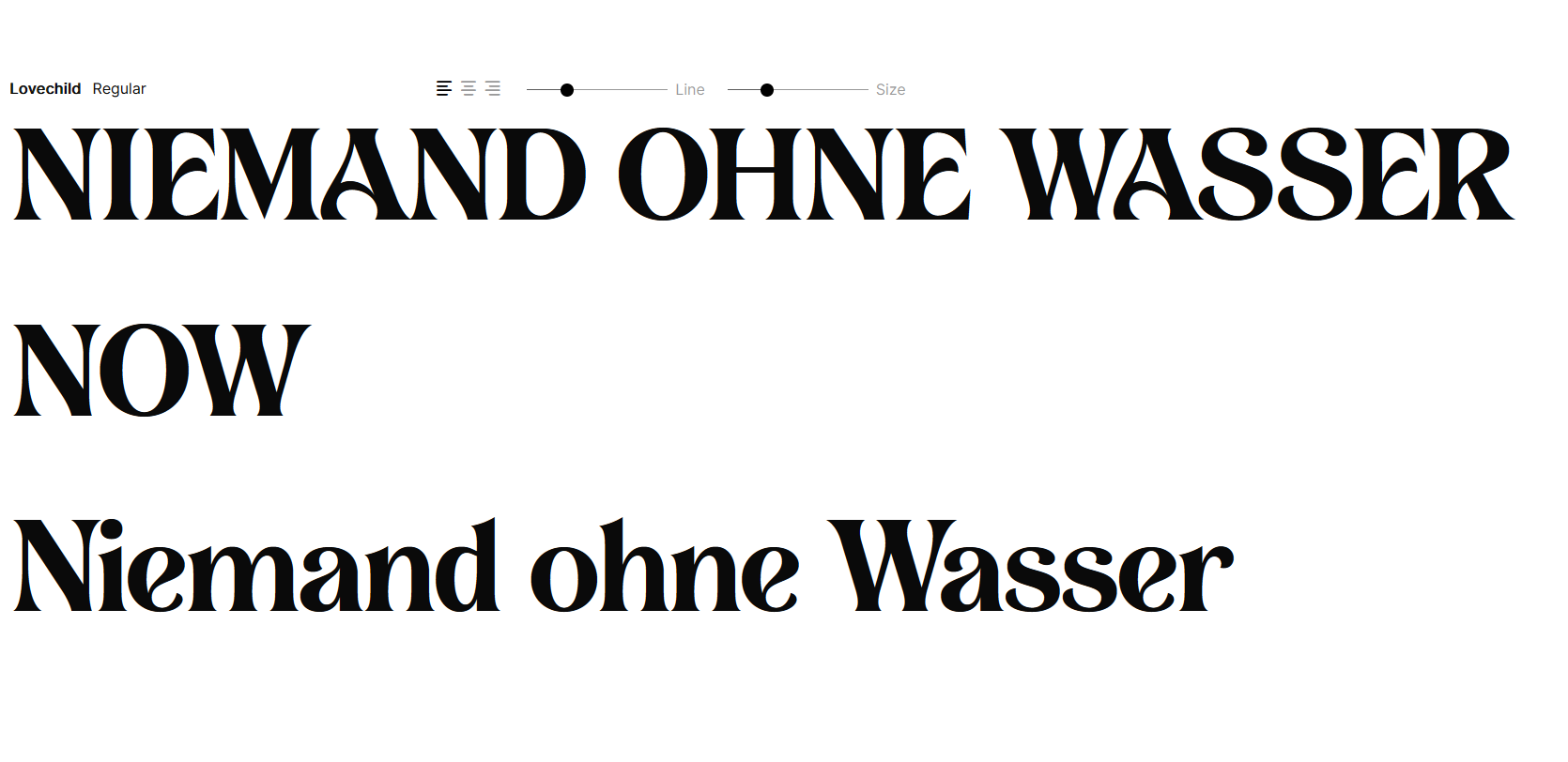
Plakative Logo-Schrift Thema Wasser.
ich mache über das Studium (Erst- bzw. Zweitsemester 😅) zusammen mit zwei Kommilitoninnen an einem Pitch mit. Das Thema ist "Wasser für die Welt". Unser Slogan lautet "Niemand ohne Wasser - NOW" . Wir würden uns freuen, wenn ihr einen Tipp für die Typo habt. Wir haben bis jetzt nur grobe Entwürfe, wie z. B. den hier:
Danke. Die Lovechild sieht cool aus! Ob es vielleicht jemanden möglich ist, uns den Text wie unten bitte als Vektorgrafik zu erstellen? ich hoffe, das ist jetzt nicht unverschämt. Aber als Studi-Pitch sind $38 dann etwas uncool.
Hallo @holgi, was genau ist das Produkt des Pitches und wer wird dadurch angesprochen? Für mich klingt das nach Plakat/Kampagne. Wenn dem so ist, stelle ich mir etwas »aktivistischeres« vor.
Die Lovechild ist zwar flüssig und hat »fließende« Elemente, spricht für mich aber eher eine zeitgenössische Beauty-/Kosmetik-Sprache (Stichworte Gesichtswasser, Rasierwasser …).
Fließende Formen mit plakativem Duktus findest du zum Beispiel in der Glance Sans (hier vor allem Black oder Black Italic). Das stencil-artige Aussehen kann den aktivistischen Eindruck verstärken – je nach typografischer Gestaltung.
Falls dir keiner die Vektoren zusenden kann: für nichtkommerzielle studentische Pitches kannst du bei vielen Foundries kostenlose, aber zweckgebundene Lizenzen anfragen. Wenn hingegen Geld im Spiel ist, sieh die knapp $13 für jeden von euch als (eigentlich nicht sehr großes) Investment an.
Wir möchten Plakate und Postkarten erstellen. Es ist für eine entwicklungspolitische Non-Profit-Organisation, welche sich für Zugang zu (sauberem) Wasser einsetzt. Es geht also um Spenden bzw. Aufmerksamkeit.